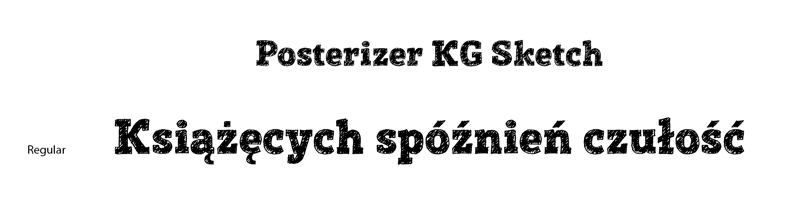
Font Posterizer KG Sketch
Do naszego studio trafił ozdobny font Posterizer. Został zaprojektowany w 2013 roku przez Lazara Dimitrijevića z Serbii. Litery fontu mają postać kształtów zamalowanych szybko grubym pisakiem.